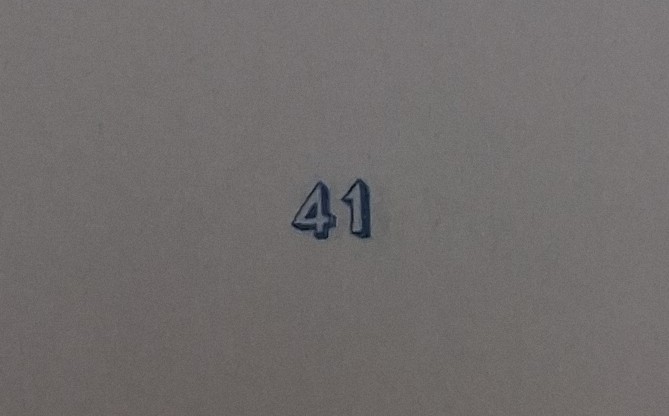
이 숫자 폰트 뭘까요 cur*** 2026.07.30 아마 무료 폰트이지 않을까 싶은데 Rampart One 폰트도 아니고 Londrina Shadow도 아니고 도저히 못 찾겠네요... 숫자에 들어간 옆면 그림자?도 있어서 나름 특징적인 폰트 같은데 의견 구합니다!! 댓글 0 등록 쉽고 빠르게 가장 비슷한 폰트를 알고 싶다면? 이미지로 검색하기
숫자에 들어간 옆면 그림자?도 있어서 나름 특징적인 폰트 같은데 의견 구합니다!!